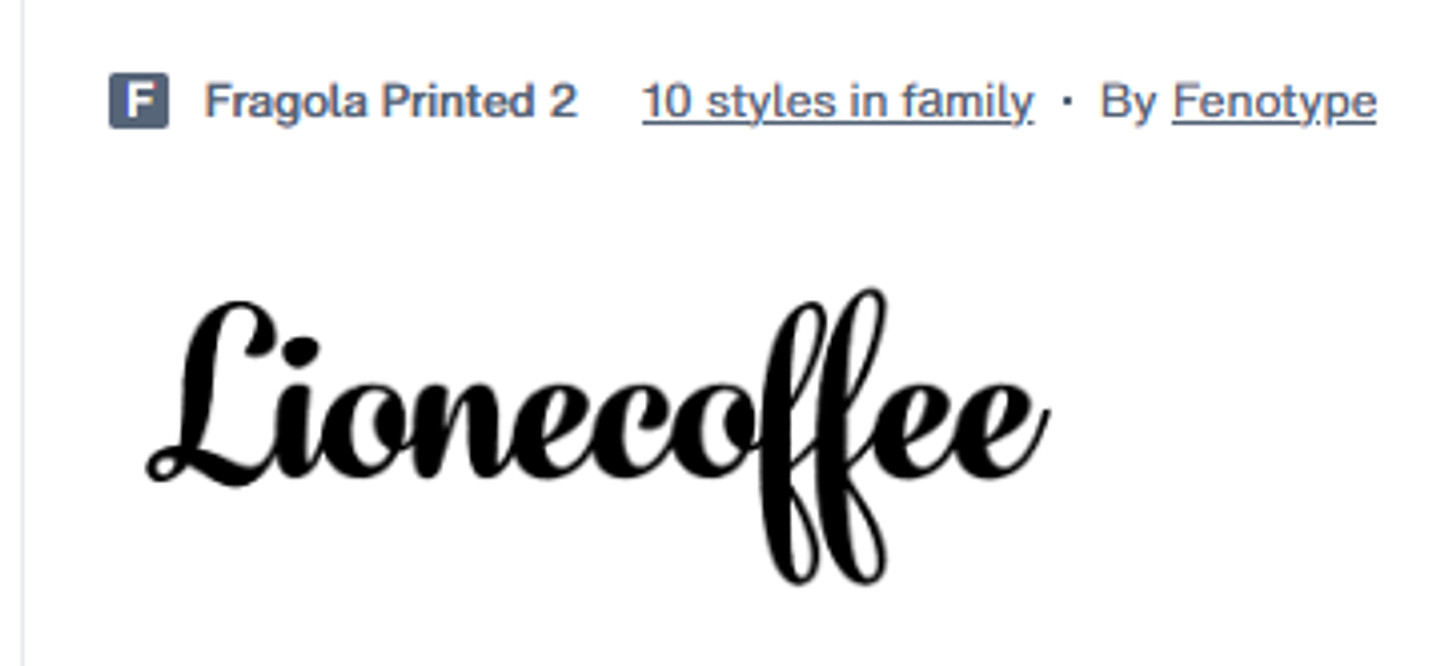
Fragola Printed2
안녕하세요! 똑같은건 안보이네요ㅠ 제가 찾은거 중에 제일 비슷한거라도 괜찮으시다면 보내드립니다! https://www.myfonts.com/products/printed-2-fragola-179001?queryId=adcfe24a7f54a5c3c568f06ed5cb55ba&index=universal_search_data&objectIDs=8595234001
친근하고 귀여운 손글씨 스타일: 정돈된 디지털 폰트보다는 사람이 손으로 직접 쓴 듯한 자연스럽고 따뜻한 느낌을 주는 서체입니다. 둥근 모서리 처리: 거의 모든 획의 끝부분이 각지지 않고 부드럽게 둥글게 처리되어 있어 전체적으로 유하고 다정해 보입니다. 일정한 굵기: 각 글자를 구성하는 획의 굵기가 대부분 일정하며, 굵은 붓펜이나 두꺼운 사인펜으로 쓴 듯한 안정감을 줍니다. 높은 가독성: 손글씨 스타일임에도 불구하고 각 자음과 모음의 형태가 뚜렷하게 구분되어 있어 읽기가 매우 쉽습니다.